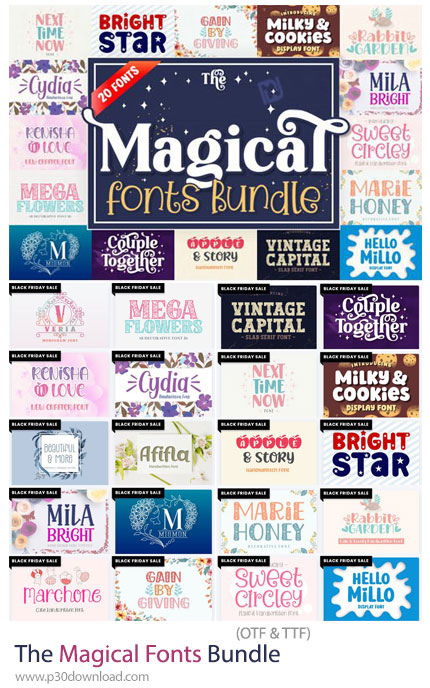
The Magical Fonts Bundle یک مجموعه فوقالعاده و الهامبخش از فونتهای فانتزی و جادویی است که برای خلق طراحیهایی با حالوهوای رمزآلود، افسانهای، رویایی و هنری ساخته شدهاند که با فرمت OTF بر روی سایت برای دانلود قرار گرفته است. اگر میخواهید پروژههای شما حس جادو، خیالپردازی و زیبایی بصری بیشتری داشته باشد، این مجموعه دقیقاً همان چیزی است که نیاز دارید. این پکیج شامل چندین فونت جذاب با سبکهای متفاوت است؛ از تایپفیسهای الهامگرفته از داستانهای فانتزی و افسانههای کلاسیک گرفته تا فونتهای مدرن با اِلِمانهای جادویی و خاص. فونتهایی که ظاهر جادویی و افسانهای واقعی داشته باشند، همیشه کمیاباند. این مجموعه با دقت و ظرافت طراحی شده تا درست همان حس جادویی و اسرارآمیز را منتقل کند. با این پکیج، شما یک کتابخانه کامل برای انواع پروژههایی که نیاز به حس خیالپردازی دارند در اختیار دارید.